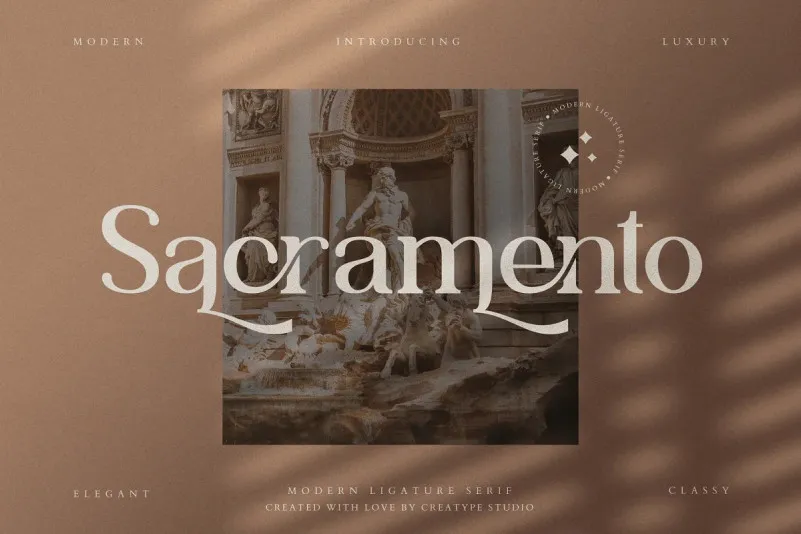
Sacramento Serif Font – Download Grátis
A Sacramento Serif Font é uma elegante escolha para aqueles que buscam um charme retrô nos seus projetos digitais. Criada pela equipe da Creatype Studio na 99designs, essa fonte serif oferece um visual único e sofisticado, garantindo que seu design ou produto seja memorable e de alta qualidade. Com uma variedade de ligações e alternativas, a Sacramento Serif Font cria um tom de classe em qualquer projeto, seja ele para gráficos, identidades corporativas ou sites. Essa fonte é perfeita para quem busca não apenas estilo, mas também um toque de elegância clássica que durará ao longo do tempo. Experimente a Sacramento Serif Font e dê vida a seus projetos digitais com um touch de sofisticação.